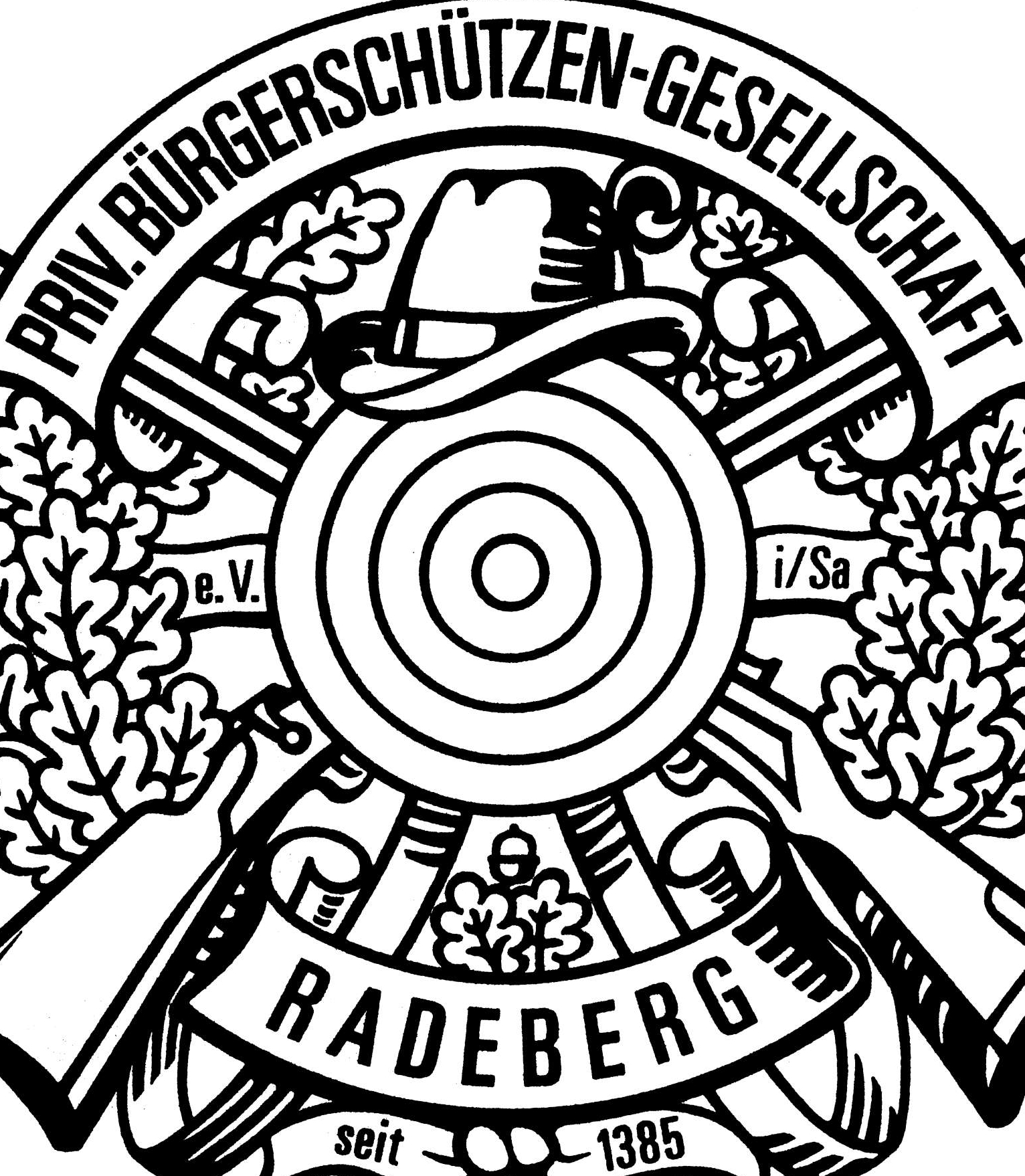
Welche Schrift ist im Vereinswappen?
ein Vereinskamerad ist dabei, unser Wappen als Vektorgrafik zu erstellen. Dazu müssten wir noch wissen, welche Schriftart im Wappen verwendet wurde, da er bisher nicht fündig wurde.
Unser Wappen ist Anfang der 90er Jahre - wohl von Hand - erstellt worden; den Ersteller können wir leider nicht ausfindig machen.
Wir suchen diesen oder einen sehr ähnlichen Font. Es wäre toll, wenn Ihr uns unterstützen könntet.
das geht Richtung Universe Compressed oder Condensed. Die Univers ist von Adrian Frutiger.  Schau auch mal auf die ähnlichen Schriften. Hier der Einstiegspunkt für den ersten Überblick:
Linotype Univers Compressed
Designers: Adrian Frutiger and Linotype Design Studio
Year: 1957, 1999
Publisher: Linotype